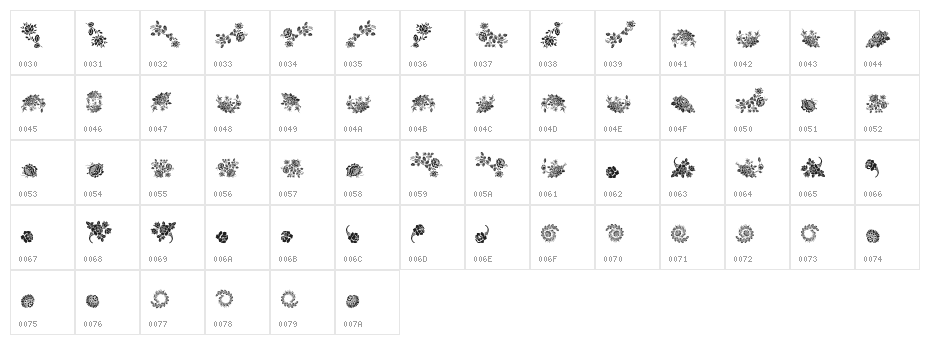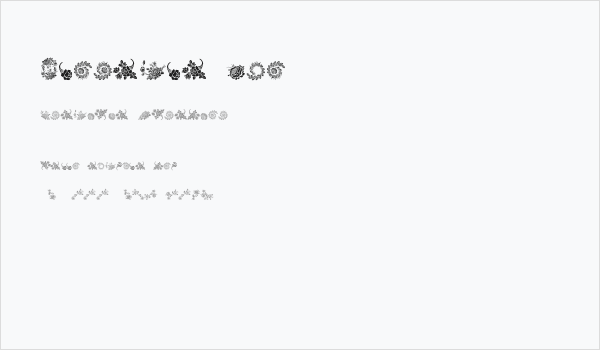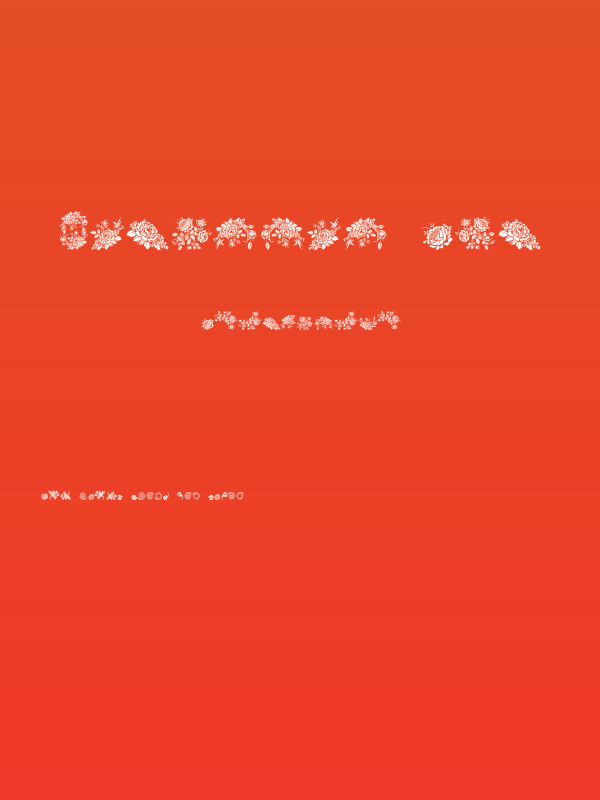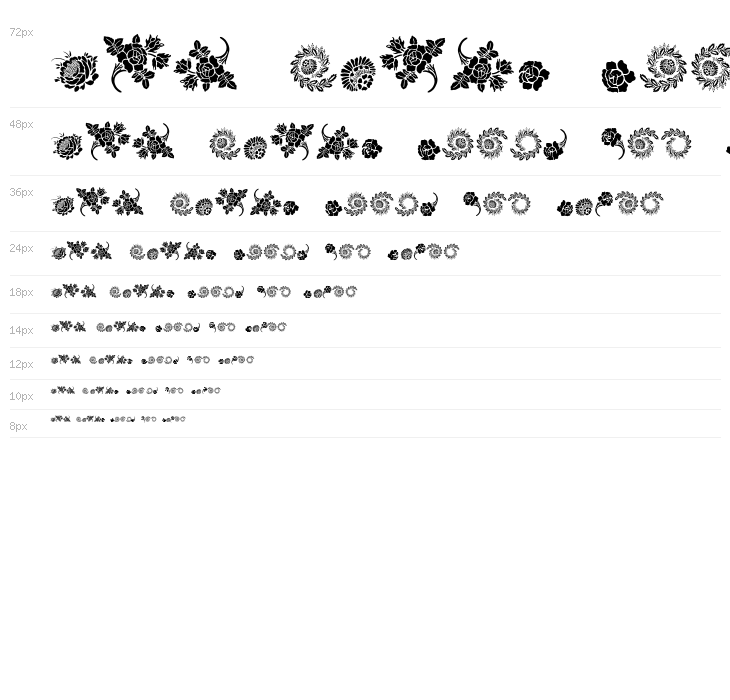
Floreale Two Font
| Gesamtstil | Decorative, Vintage, Ornamental |
| Anwendungsfall | Borders, embellishments, decorative accents |
| Vorgeschlagene Projekte | Wedding invitations, decorative borders, packaging, greeting cards, scrapbooking, branding for florists. |